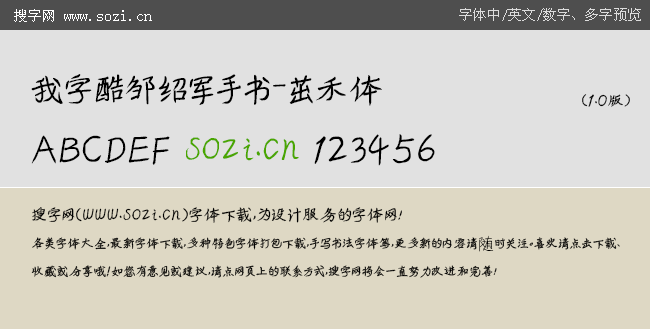
我字酷鄒紹軍手書-茁禾體
搜字網(wǎng)提供一款我字酷鄒紹軍手書-茁禾體中文書法字體下載,我字酷鄒紹軍手書-茁禾體是一款手寫風(fēng)格的鋼筆書法字體,字體書寫流暢,字形大方,整體效果十分出色,適合應(yīng)用于廣告設(shè)計(jì)、名片設(shè)計(jì)、包裝印刷、產(chǎn)品設(shè)計(jì)等應(yīng)用。